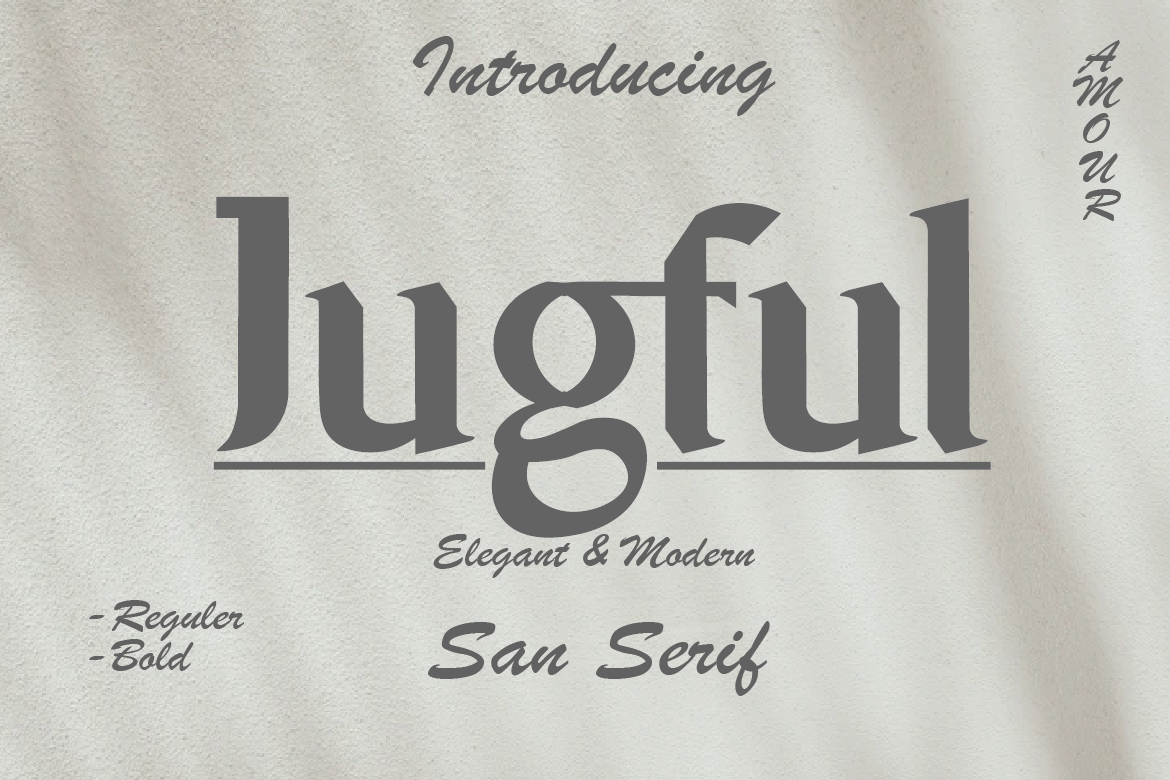
Jugful Font
A fonte ‘Jugful Font’ é uma elegante família de tipo serif que se destaca por sua simplicidade e limpeza. Inspirada no design serif, a fonte oferece um contraste gráfico perfeito para ambientes de marca forte e clássicos, tornando-a uma opção versátil para uma ampla gama de projetos. Suas linhas suaves e detalhes delicados permitem que seja utilizada não só em criações digitais como websites e logotipos, mas também em impressões, embalagens de produtos e materiais de decoração casuais. Seja para criar um design moderno para vídeos ou embutir uma nota personalizada no site de uma cerimônia de casamento, a fonte ‘Jugful Font’ traz vida à sua ideia ao unir simplicidade com elegância. Combinar essa família de tipo com as obras da Design Amour certamente resultará em criações memoráveis e sofisticadas.
Designer: Design Amour